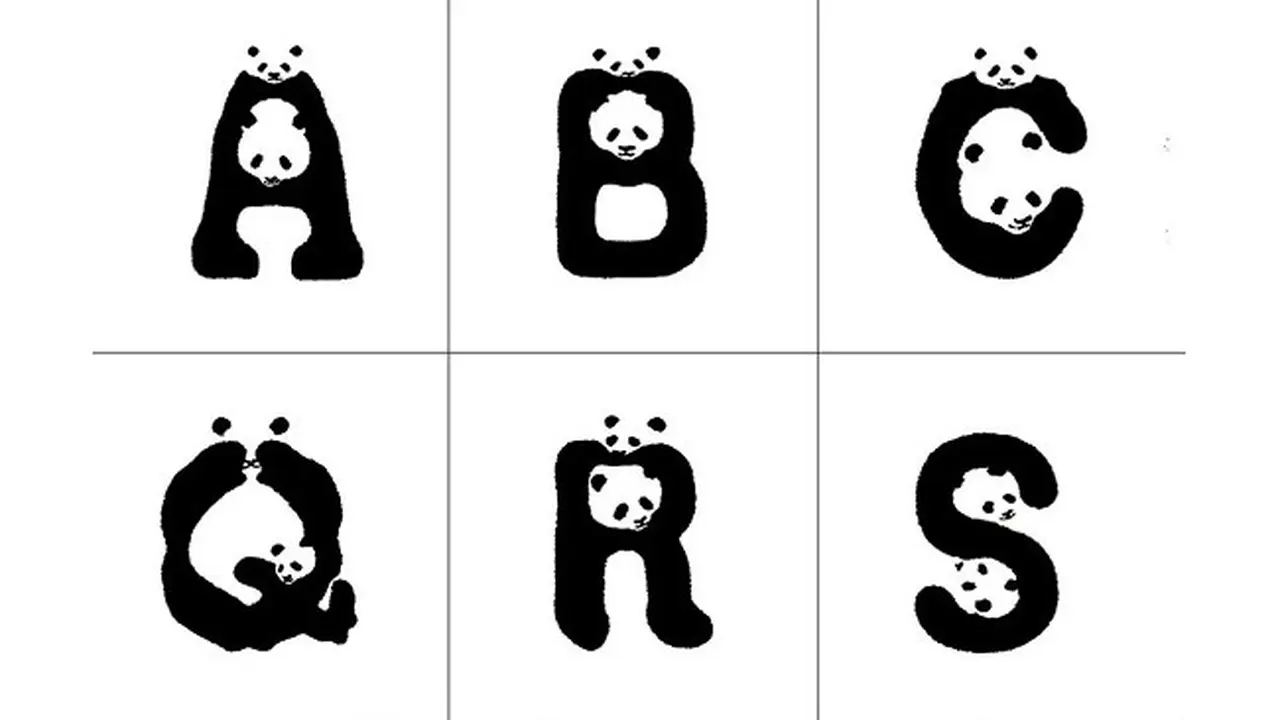
Artinya, panda sudah menjadi hewan langka yang dilindungi. Untuk mengajak masyarakat meningkatkan kepedulian masyarakat akan isu ini, dan juga untuk menggalang dana donasi, WWF baru-baru ini meluncurkan font panda. Setiap huruf merupakan modifikasi bentuk kepala panda. Desainnya merupakan hasil kerjasama dengan Ogilvy & Mather Jepang, seperti dilaporkan dari boredpanda.com, Selasa (26/5/2015).
Dengan menggunakan font ini, Anda akan membantu meningkatkan kepedulian, dan diharapkan ada perubahan besar dalam usaha pelestarian hewan langka.